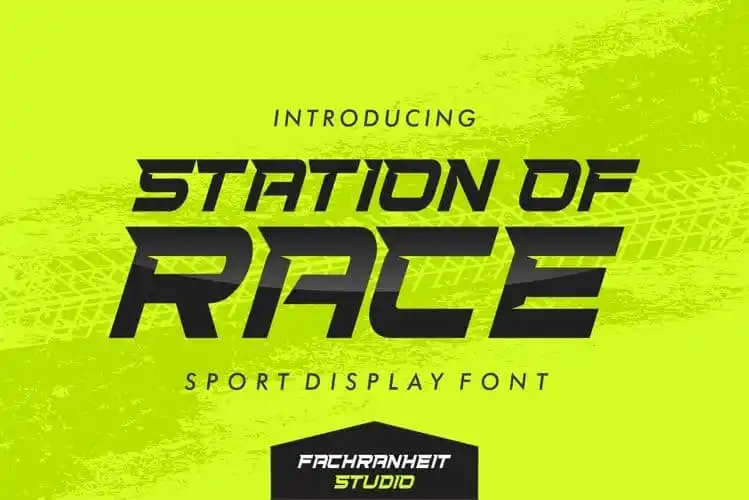
A Station Of Race Display Font é uma escolha elegante para qualquer projeto que exige presença visual forte e estilo moderno. Essa tipografia geométrica se destaca com suas formas retangulares, criando um aspecto robusto e atemporal. O uso de caracteres maiúsculos e minúsculos permite uma grande flexibilidade ao usar a fonte em diversas aplicações, incluindo mensagens de quote, designs para camisetas, folhetos promocionais, canais do YouTube, rótulos, logomarcas, embalagens customizadas e até mesmo em materiais de marca. Com a presença única da Station Of Race, é perfeitamente adequada para criar um impacto imediato sem comprometer a legibilidade. A adição de caracteres ligados, alternativas estilísticas e símbolos monetários torna ainda mais versátil seu uso em qualquer projeto visual que você possa imaginar.